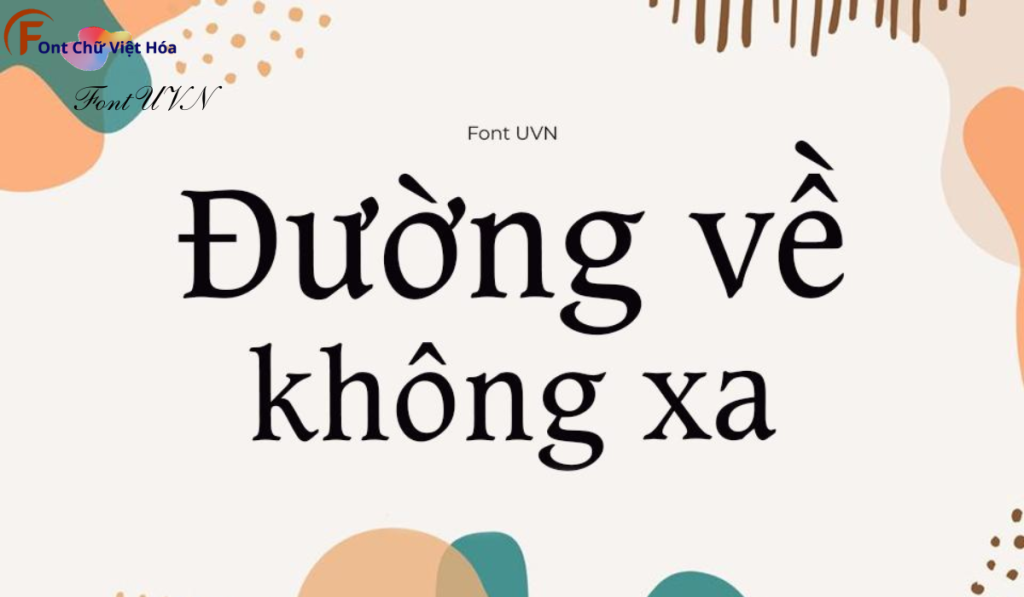
Font UVN Cát Biển Việt Hóa
Phân loại: Cá tính, Độc đáo
Kiểu chữ: Có chân
Độ dày: Thường
Font UVN Cát Biển Việt Hóa là một font chữ có chân hiện đại, thuộc bộ font UVN. Được thiết kế với mục tiêu mang lại sự tinh tế và thanh lịch, font này phù hợp cho các dự án thiết kế như website, tài liệu, và bao bì sản phẩm. Với các nét chữ rõ ràng và độ dày đều đặn, Font UVN Cát Biển Việt Hóa không chỉ dễ đọc mà còn tạo cảm giác chuyên nghiệp.